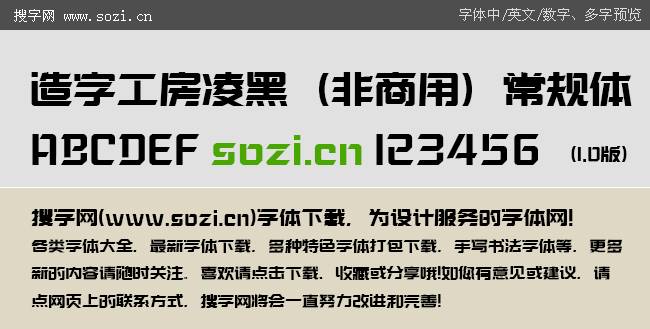
造字工房凌黑(非商用)常規(guī)體
搜字網(wǎng)提供一款造字工房凌黑(非商用)常規(guī)體中文字體下載,造字工房凌黑常規(guī)體字形飽滿、整體風(fēng)格粗曠厚重,字重渾厚、棱角分明,結(jié)構(gòu)方正沉穩(wěn)不失時(shí)代氣息,橫的切角處理讓字體更顯剛毅。筆畫與筆畫間的斷層處理,使其筆畫頓挫有力、峻拔剛斷、有抑揚(yáng)頓挫之感。給整體字形帶來很強(qiáng)的現(xiàn)代科技感。此款字體適用于主副標(biāo)題及個(gè)性品牌的設(shè)計(jì)等應(yīng)用。